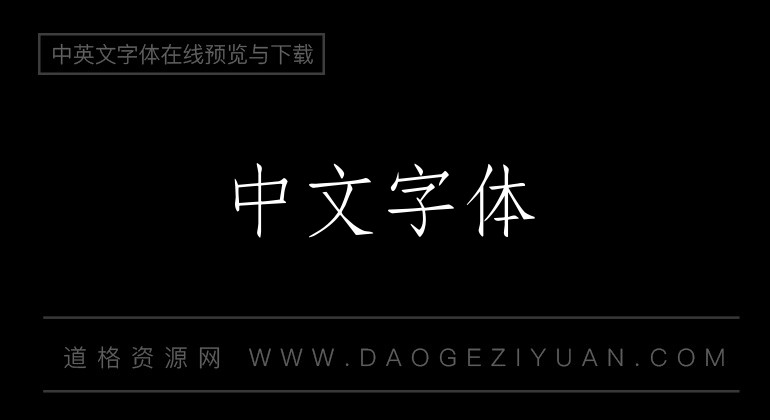
超世纪中仿宋体繁是一款由超世纪字体研究院出品的中文字体,它是以宋体为基础,模仿宋体繁体字的字体。超世纪中仿宋体繁字体采用精确的技术,以宋体繁体字作为原型,以“中仿宋体繁”的名称重新设计,以便更好地体现宋体繁体字的特点。它具有清晰的笔画、稳定的结构、优美的曲线和完美的笔划,是一款非常优秀的中文字体。文件名:ChaoShiJiZhongFangSongTiFan-1.ttf
超世纪中仿宋体繁是一款非常不错的手写艺术字体,具有很好的视觉感,适合于文化类的宣传设计、商业类品牌的广告和产品包装设计以及个性化文字排版等较多场景。